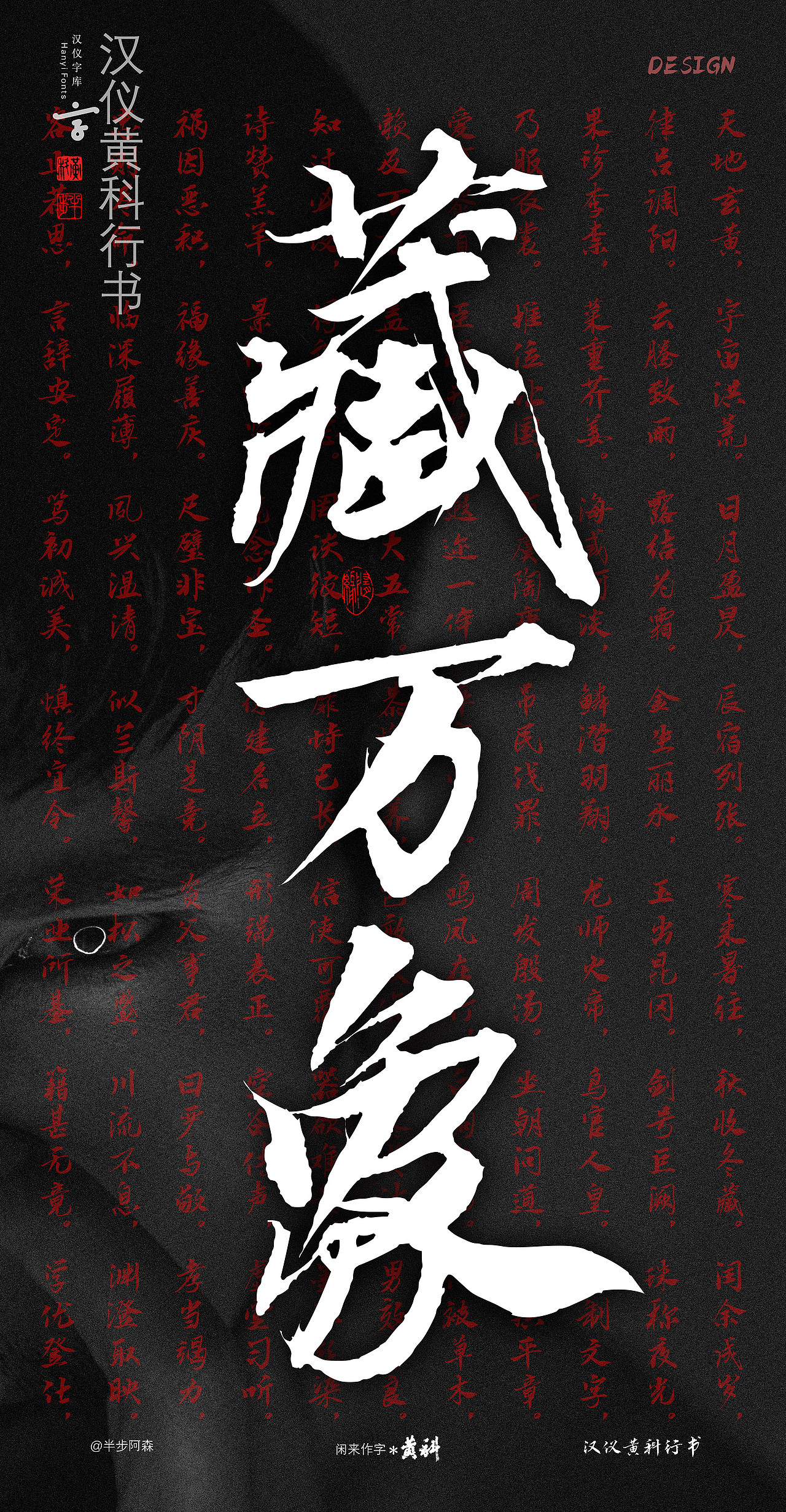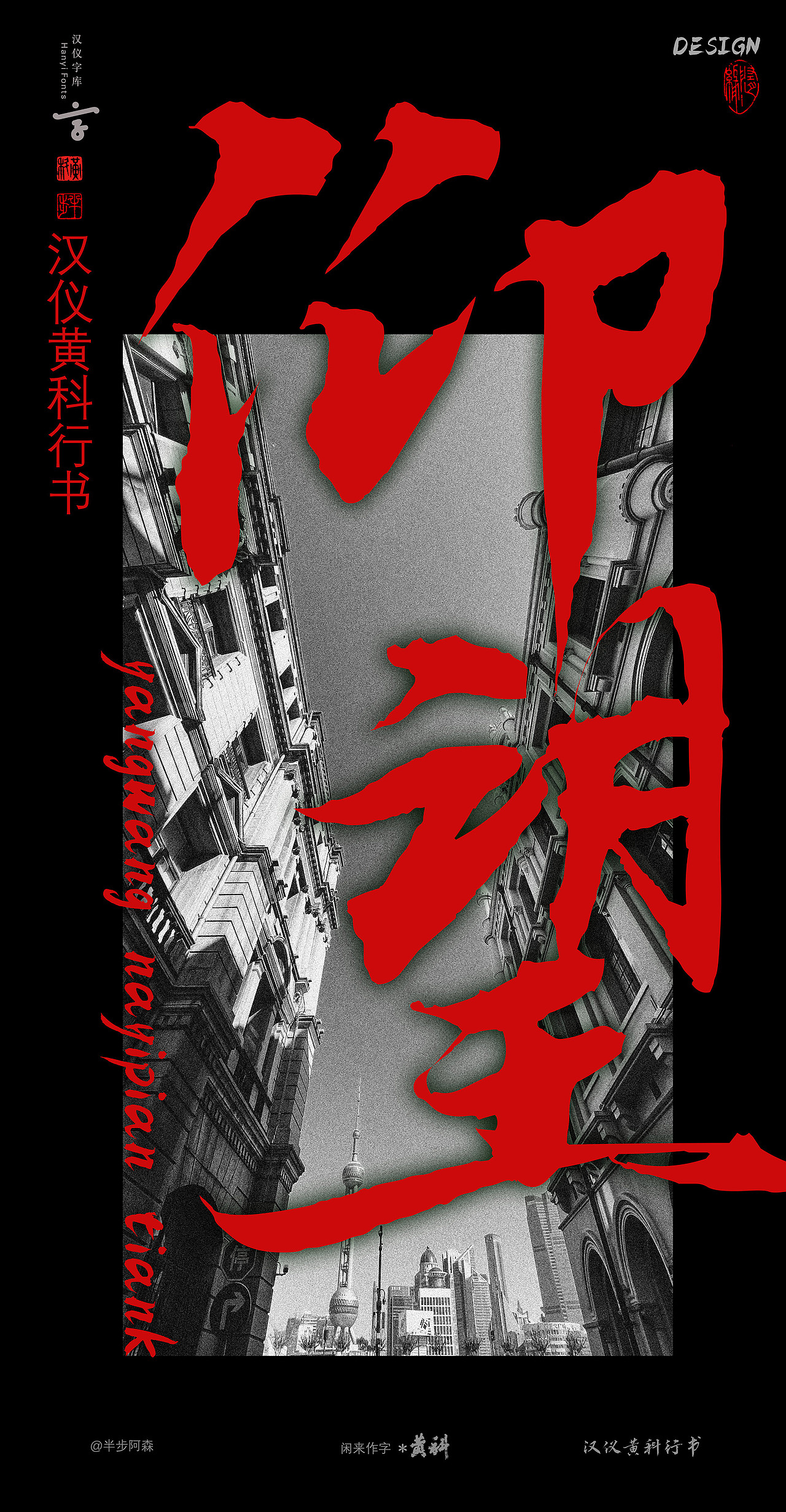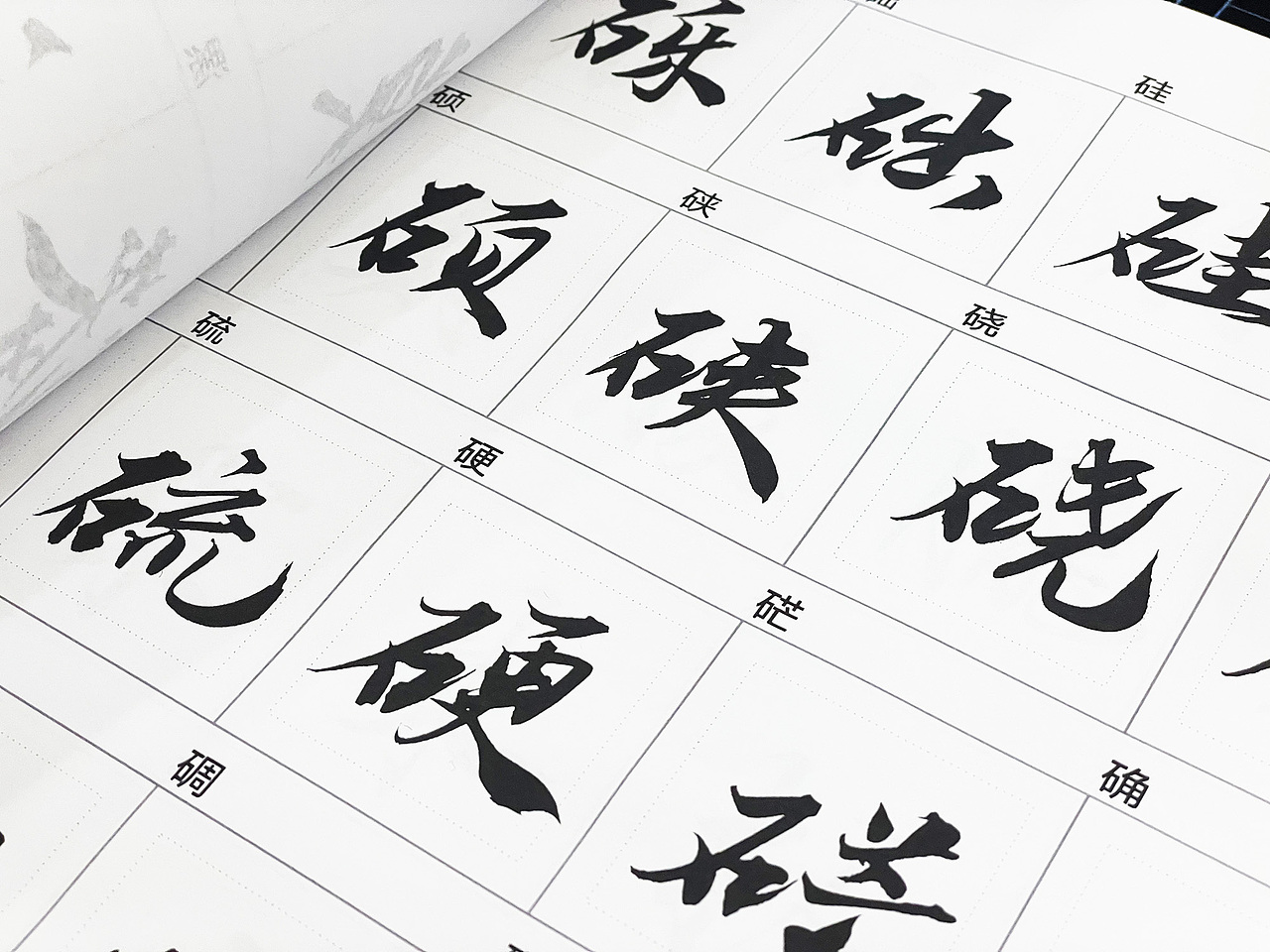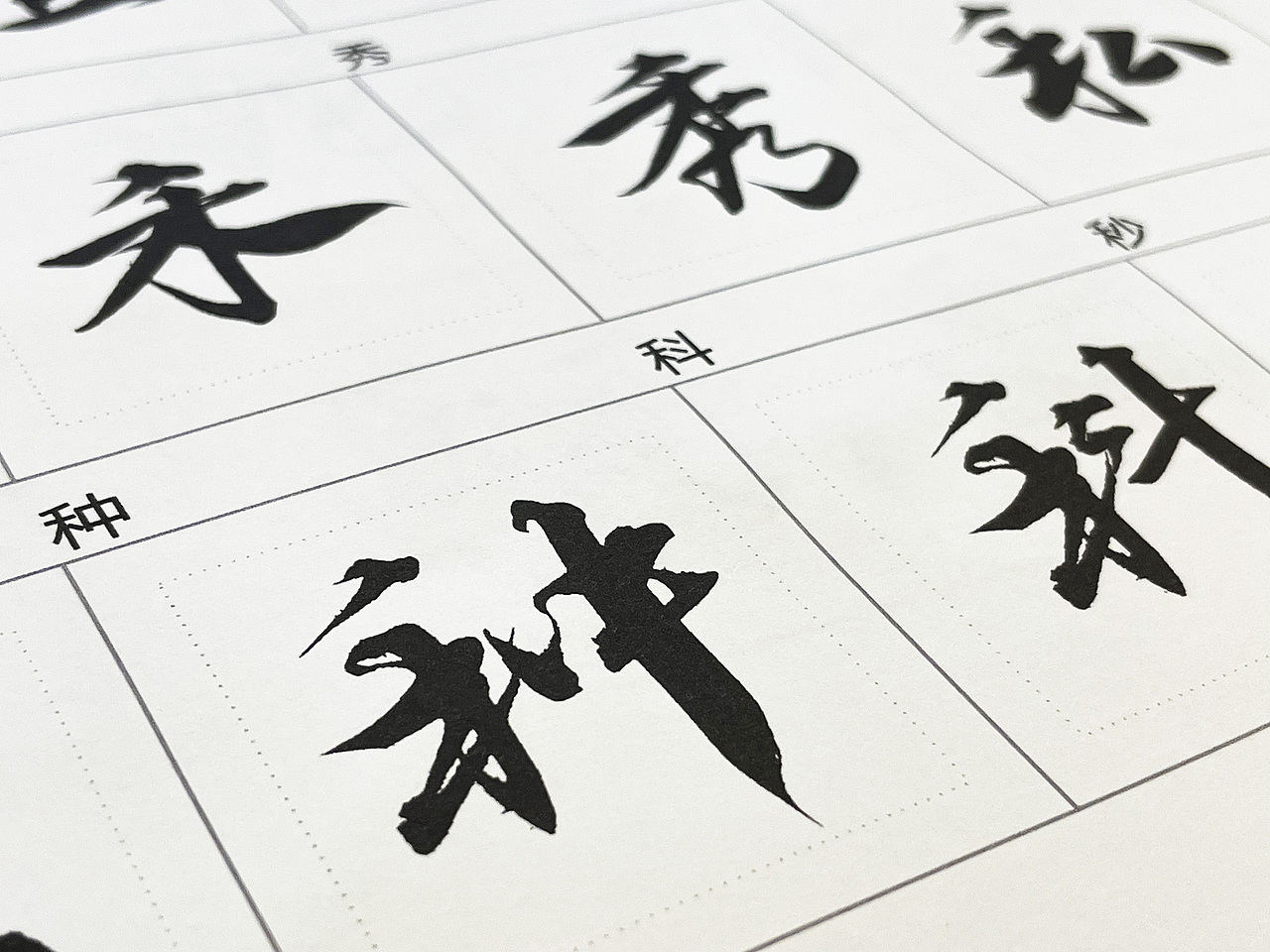
汉仪黄科行书(新字库上架了)
汉仪黄科行书是我历两一年完成的第二套字库,完全区别于第一套黄科汉仪榜书。风格上俊秀利落,锐利中稍带柔美。
起笔收笔以露锋为主呈现小字外放的感受,线条曲直交替,多牵丝连带关系,进一步强化粗细对比。结构上平整中稍带跳跃,整体视觉感受轻盈灵动。
逐字放大后有细节,局部放大之后有较强的装饰功能。较宜纵向排列或打散交替排列使用。敬请大家指正。